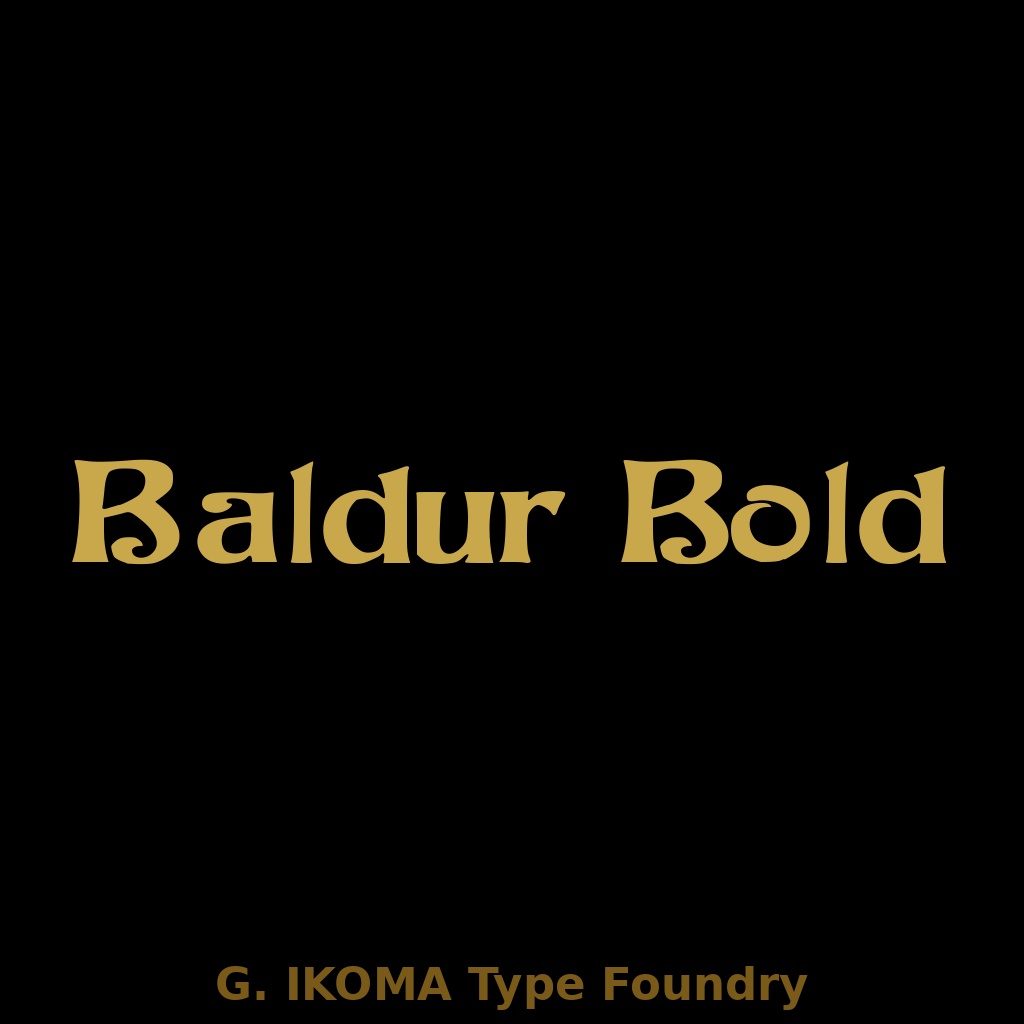
BALDUR — 19世紀欧州印刷資料復元フォント / Historical Revival Typeface [Gothic / Jugendstil]
━━━━━━━━━━━━━━━━━━━━━━━━━ 【フォントについて】 ━━━━━━━━━━━━━━━━━━━━━━━━━ **BALDUR** は、19世紀末〜20世紀初頭の欧州印刷資料を原典に、手作業でトレース・デジタル化した復元フォントです。 本作は、ライプツィヒの活字鋳造所 **Schriftgiesserei Julius Klinkhardt** による Gothic / Jugendstil 系書体をもとに再構成したものです。原典資料上部には **「BALDUR · SCHRIFTGIESSEREI JULIUS KLINKHARDT, LEIPZIG.」** と記されています。 Nordic・Gothic 系の力強い骨格と、Jugendstil 的な装飾性をあわせ持つ、太字ディスプレイ書体です。 **原典**:Ludwig Petzendorfer, *Schriften-Atlas* または *Schriften-Atlas: Neue Folge* Julius Hoffmann, Stuttgart(パブリックドメイン) **様式**:Gothic / Jugendstil **収録文字**:大文字 A–Z、小文字 a–z、数字 0–9、記号類 **欠落文字**:なし **制作**:株式会社生駒時計店 / G. IKOMA, LTD.(1870年創業) ━━━━━━━━━━━━━━━━━━━━━━━━━ 【ご購入前にご確認ください】 ━━━━━━━━━━━━━━━━━━━━━━━━━ 本フォントは、力強い骨格と装飾性を特徴とする **ディスプレイ向け書体** です。 ロゴ、見出し、タイトル、パッケージ、映像用テロップなどには適していますが、本文組版や小サイズでの長文用途には向きません。 また、原典由来の字形をもとに再構成しているため、現代的な本文用書体のような汎用性を前提とした設計ではありません。 ━━━━━━━━━━━━━━━━━━━━━━━━━ 【収録内容】 ━━━━━━━━━━━━━━━━━━━━━━━━━ ・BALDUR.ttf ・LICENSE.txt ━━━━━━━━━━━━━━━━━━━━━━━━━ 【推奨用途】 ━━━━━━━━━━━━━━━━━━━━━━━━━ ・ロゴ ・見出し ・ゲームタイトル ・映像テロップ ・パッケージデザイン ・招待状 ・装丁 ・ラベル ・バナー画像 ・サムネイル画像 **装飾性と力強さを活かすディスプレイ用途** に適しています。 本文組版や小サイズでの常用には向きません。 ━━━━━━━━━━━━━━━━━━━━━━━━━ 【ライセンス】 ━━━━━━━━━━━━━━━━━━━━━━━━━ 本フォントは、**個人利用・商用利用を問わず**、印刷物、画像、ロゴ、バナー、動画サムネイル等の制作に使用できます。 また、**WebサイトやSNSで画像化された状態で使用することは可能**です。 ただし、以下の行為は禁止します。 ・フォントファイルそのものの再配布、再販売、譲渡、共有 ・改変したフォントファイルの配布 ・本フォントを素材集、テンプレート、デジタル商品等に収録して再販売する行為 ・**本フォントファイルをWebフォントとしてサーバーに設置・配信して利用する行為** ・アプリケーション、ゲーム、ソフトウェア、電子機器等への埋め込み利用 ・AI学習、機械学習、生成モデル訓練等への利用 ・本フォント自体または収録字形そのものについて独占的権利を主張する行為 詳細は同梱の **LICENSE.txt** をご確認ください。 ━━━━━━━━━━━━━━━━━━━━━━━━━ 【原典資料について】 ━━━━━━━━━━━━━━━━━━━━━━━━━ 本フォントは、G. IKOMA, LTD. 所蔵の実物資料をもとに制作しています。 原典資料そのものは本商品に含まれていません。 資料アーカイブについては、下記サイトをご参照ください。 G. IKOMA Archive [https://g-ikoma-archive.netlify.app/](https://g-ikoma-archive.netlify.app/)